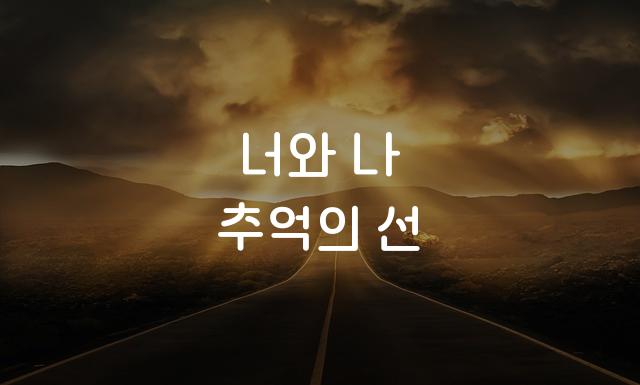
망고보드 별별체는 동글동글한 형태와 가로로 긴 구조로 독특함을 강조하는 한국어 폰트입니다. 별 모양을 연상시키는 재치 있는 디자인이 특징입니다.
망고보드 별별체은(는)
부드러움, 복실복실, 별모양/패턴, 둥근 스타일, 자연감성, 감성적인, 장식 스타일, 두꺼운 스타일, 레트로 계열의 생김새를 가지고 있으며
어린이 책, 소셜 미디어, 인사말 카드 등에서 자주 활용되며, 효과적인 메시지 전달에 적합합니다.
이 폰트는 라이프스타일, 이벤트/웨딩, 유아/가족 분야에 잘 어울리며,
재미있는, 귀여운, 친근한 느낌을 담고 있는 것이 특징입니다.